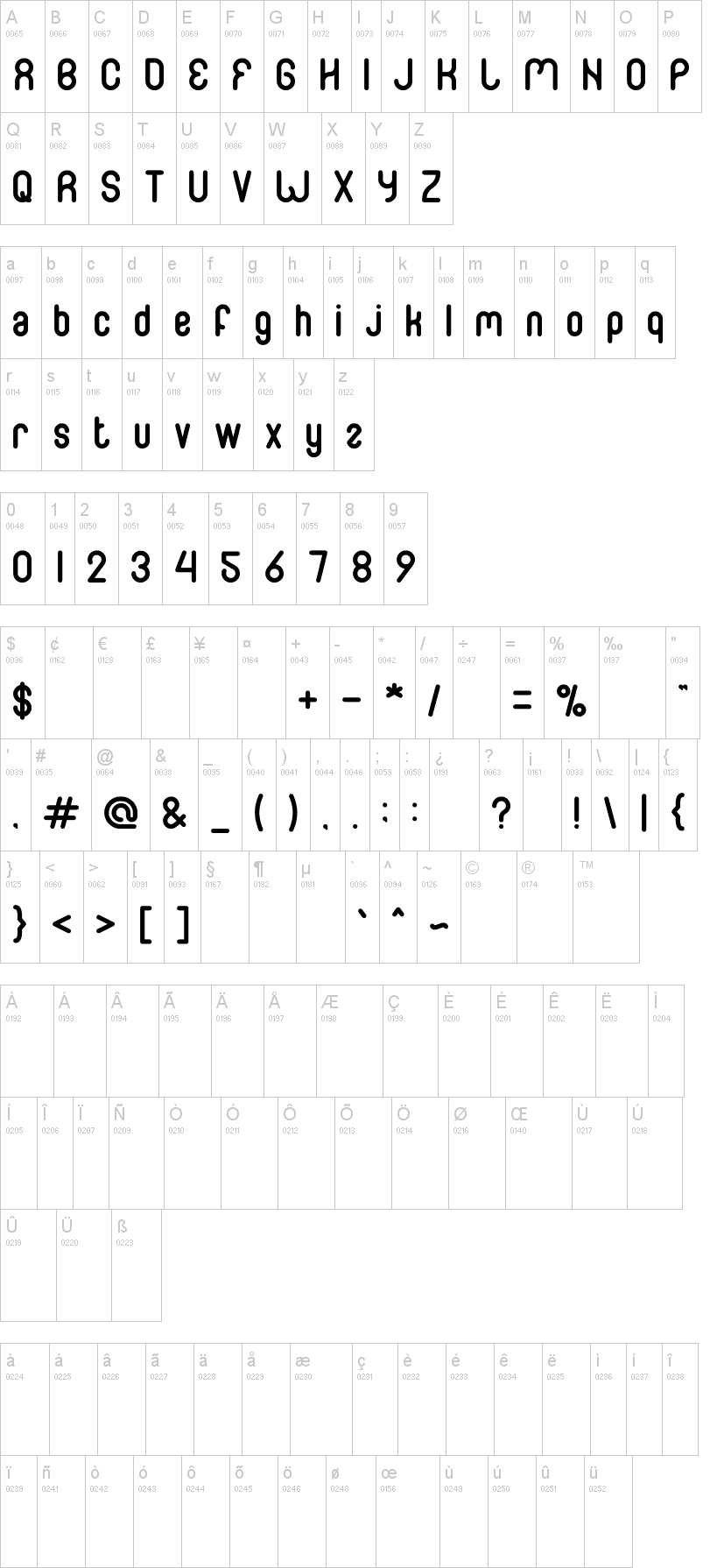
Family & Friend
Family & Friend 字体是一种温暖、简洁、友好的字体,它是由英国设计师Jimmy Kalman创作的,它的特点是细节精致,笔画细腻,字形简单,有一种温暖的感觉,可以用于各种电子产品的界面,以及广告、标识、社交媒体、网站、文档等场景。它有一种温暖、友好的感觉,可以让你的设计更加生动有趣,更容易吸引用户的注意力。
Family & Friend是一款非常不错的手写艺术字体,具有很好的视觉感,适合于文化类的宣传设计、商业类品牌的广告和产品包装设计以及个性化文字排版等较多场景。
Family & Friend字符映射图